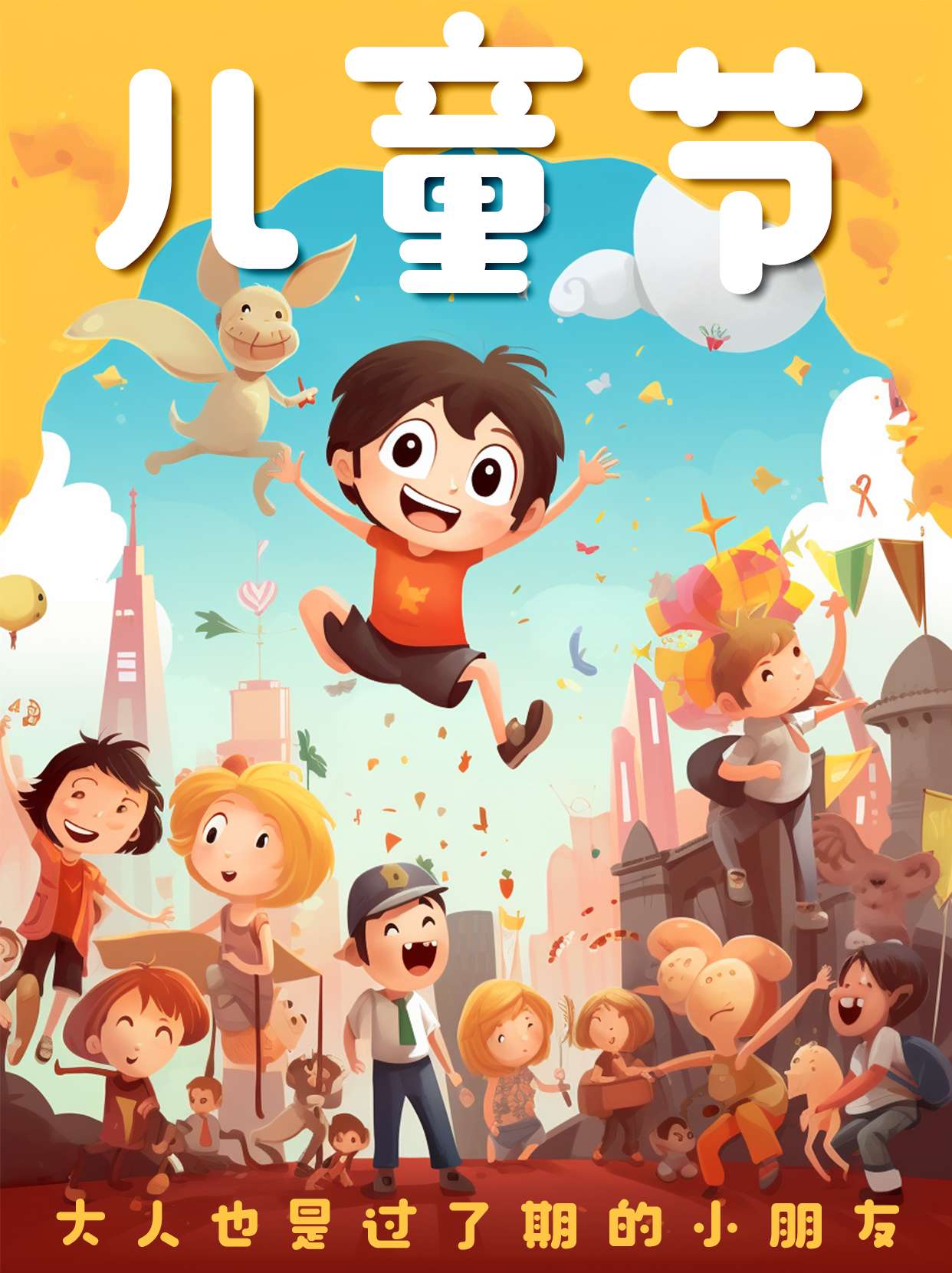
励字造桃气圆 常规
Dreams-TaoqiGBT Regular
一款以手写感为基础的圆体,字型上松下紧,重心略低,结构松弛灵活,变化多样。
整体笔形圆润饱满,舒展流畅。统一的笔画设计,折笔处内外圆角兼备,用圆形元素代替部分笔画,丰富了视觉效果。
笔画之间根据空间和位置采用了“断开”的处理方式,增加了轻快的整体风格,具有良好的视觉表现与阅读体验。